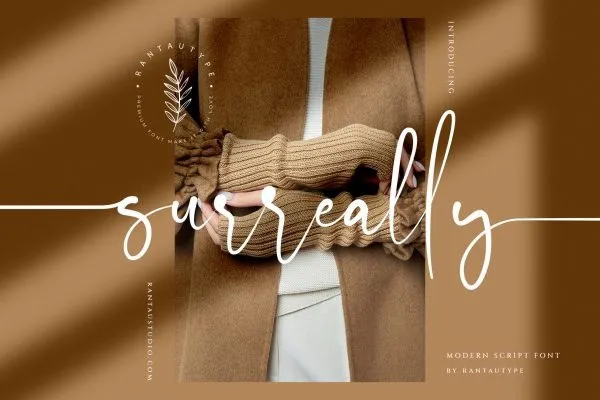
Descubra a surpreendente fonte ‘Surreally Font’, perfeita para quem busca uma mão escrita delicada e elegante. Este script font foi projetado para destacar seu estilo em qualquer projeto, seja ele um card de negócios ou um logotipo personalizado. Ideal para uso como logomarca, água-marinha na fotografia, design de letras assinatura, capas de álbum, revistas e muitos outros aplicativos gráficos. Surreally é uma escolha genial para aqueles que desejam imprimir sua assinatura com estilo. Além disso, ele também faz maravilhas em elementos de texto como citações ou tags nas redes sociais – criando um toque atraente e pessoal. Este font script foi feito pensando no seu conforto e satisfação ao longo do tempo, garantindo uma experiência visual agradável para você e seus clientes.